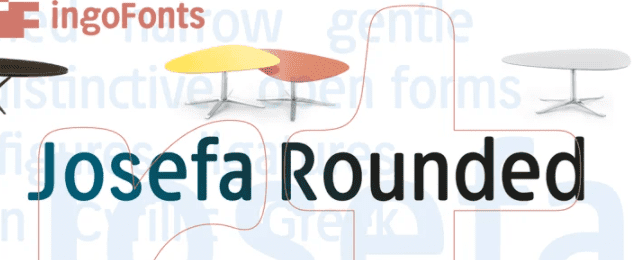
[Myfonts] Josefa Rounded Pro Font (2021)
Josefa Rounded - красивый текстовый шрифт. Его неброские формы и сбалансированные узкие пропорции вместе со смягченными круглыми краями делают его нежным и приятным даже в длинных текстах.
Индивидуальность Josefa Rounded определяют и особые идиосинкразические буквы. Например, B P и R выполнены открыто; штрихи E и F равны друг другу; строчные c и e отчетливо выведены в нижнюю зону; y симметрична.
Короткие подъемы создают компактные образы слов.
Высота прописных букв короче, чем высота подъема, поэтому прописные буквы лишь немного выше высоты.